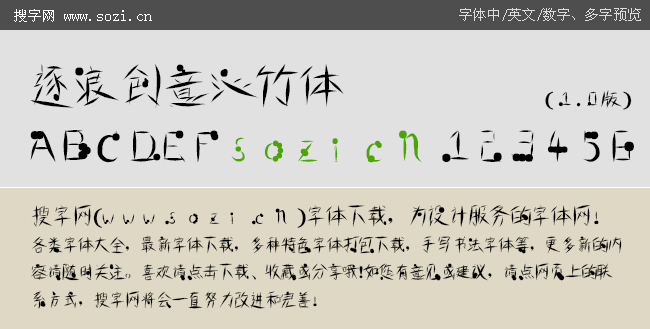
逐浪創(chuàng)意沁竹體
搜字網(wǎng)提供一款逐浪創(chuàng)意沁竹體中文藝術(shù)字體下載,逐浪創(chuàng)意沁竹體整個(gè)字形采用竹枝般的線條,從而具備脫俗清真的效果,特殊筆位會(huì)采用云朵裝飾,從而構(gòu)成完整的視覺傳播體系,適合應(yīng)用于廣告設(shè)計(jì)、名片設(shè)計(jì)、包裝印刷、產(chǎn)品設(shè)計(jì)等應(yīng)用。